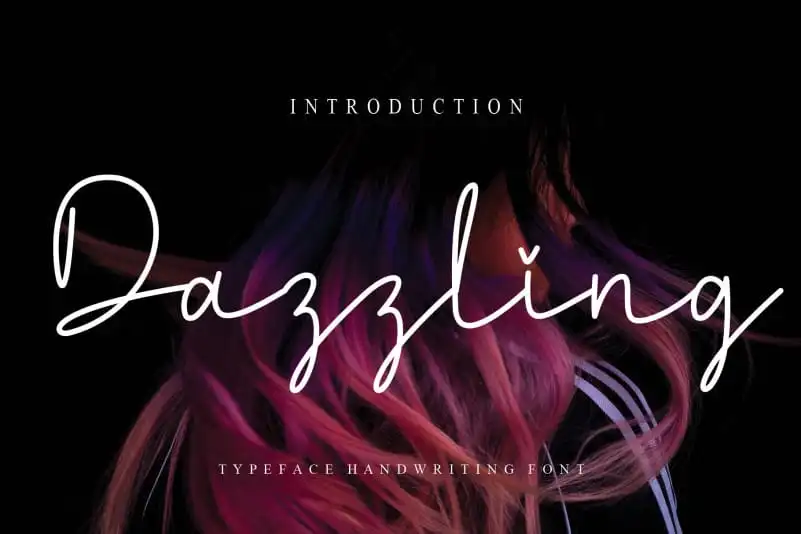
A fonte Dazzling Handwritten é uma criação única e artesanal, criada por designers talentosos para oferecer experiências memoráveis aos seus projetos. Ela traz a delicadeza de um texto real escrito à mão, mas com uma precisão que permite uso em vários formatos de conteúdo digital. Seja para criar cartões personalizados, gráficos únicos ou apenas adicionar um toque autêntico a seu design, Dazzling Handwritten está aqui para fazer sua arte mais especial ainda. Com suas linhas elegantes e movimentos fluidos, ela oferece uma textura que se aproxima da realidade, fazendo do seu trabalho algo imediatamente reconhecível e memorável. Seja qual seja o projeto à sua disposição, esta fonte será o complemento perfeito para torná-lo ainda mais notável.